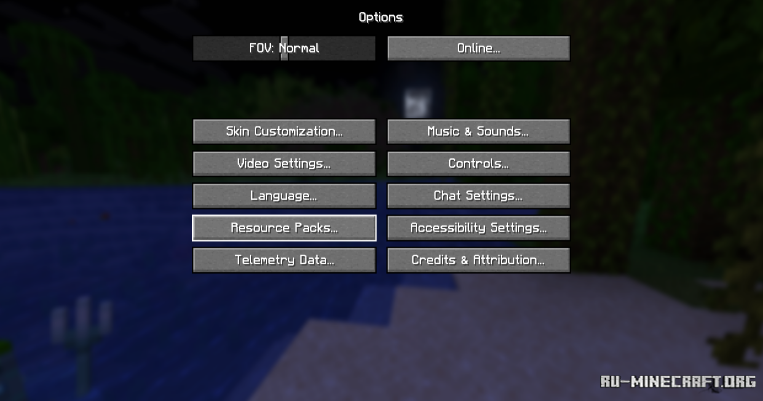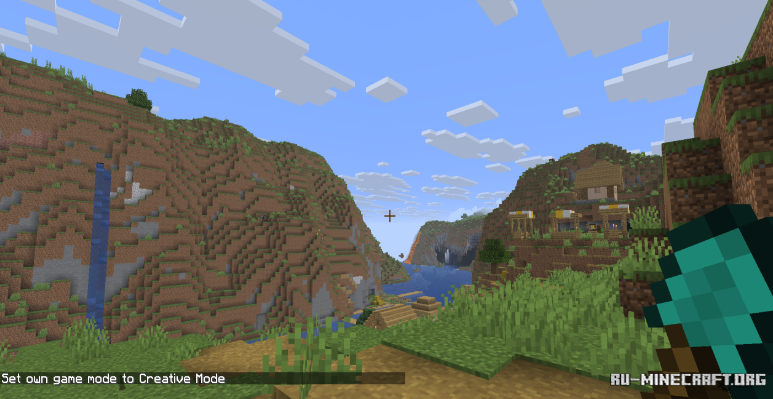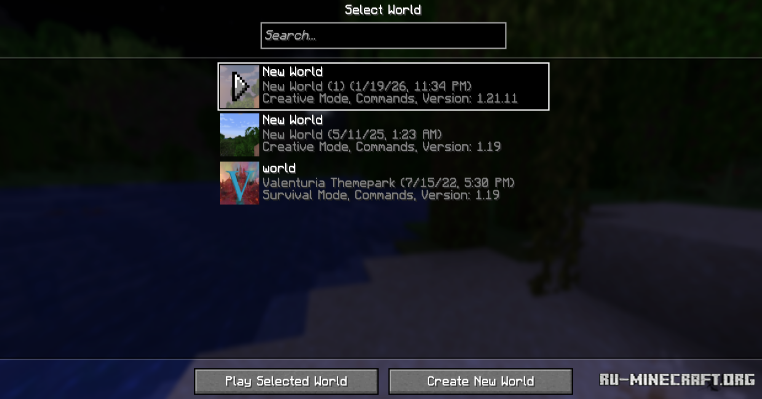
Скачать Smooth Font для Minecraft 1.21.11
Представляем вашему вниманию отличный пакет текстур Smooth Font, который вы сможете использовать для преображения привычного шрифта в некий плавный и мягкий вариант в собственной игре. Очень неплохой пакет, который открывает для вас подобные улучшения в собственной игре - вам непременно понравиться.